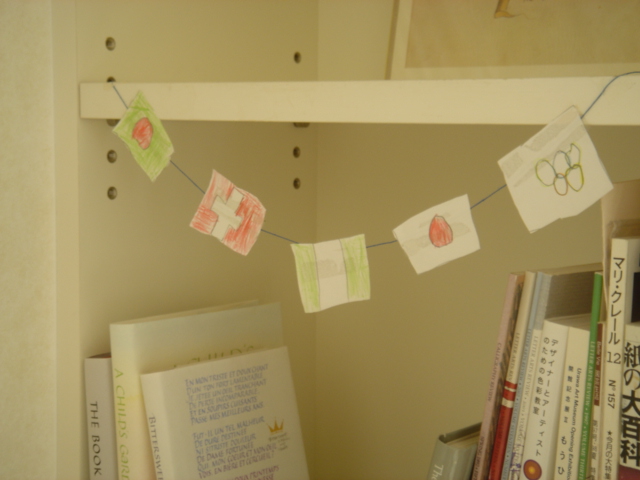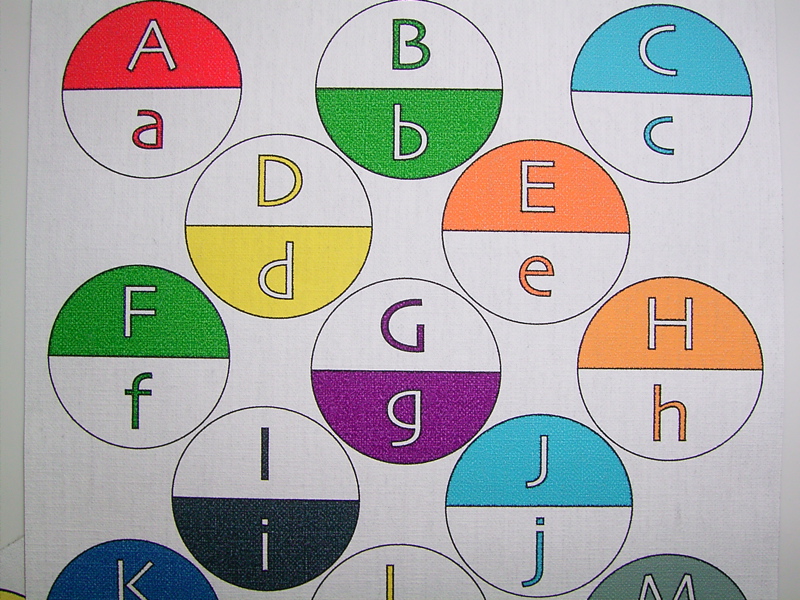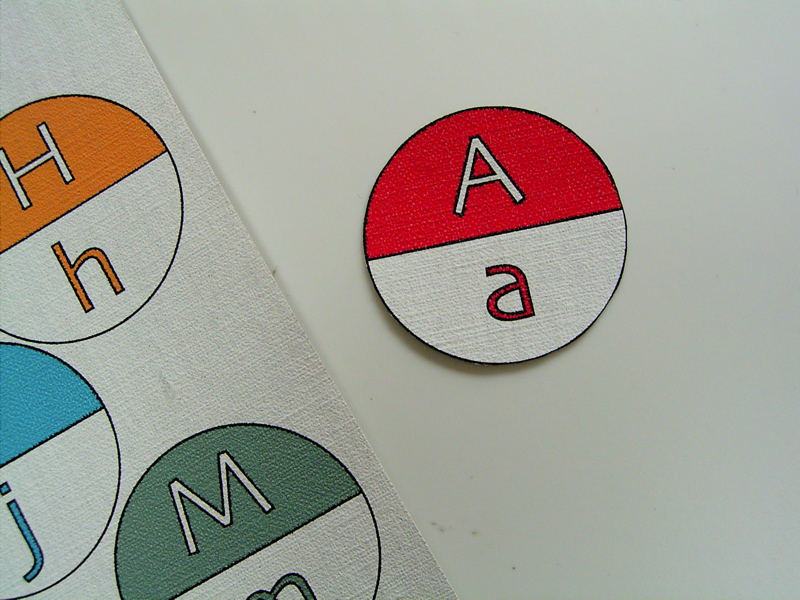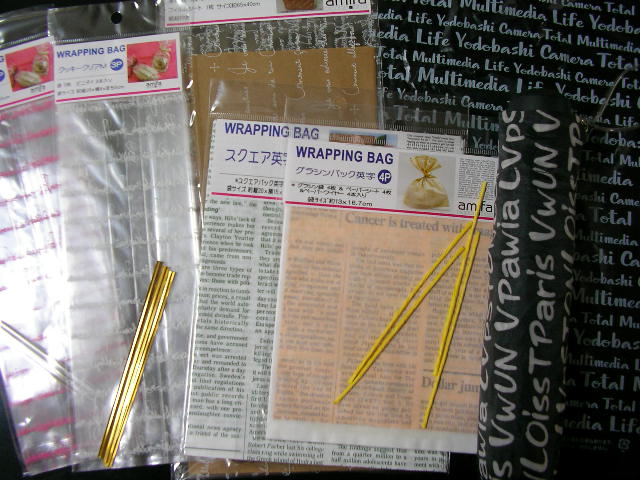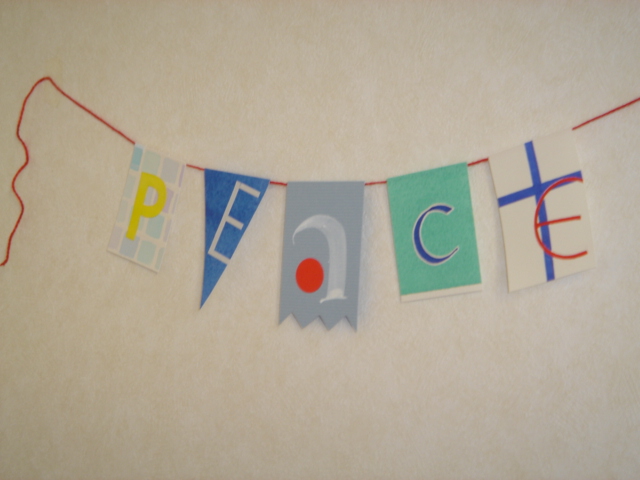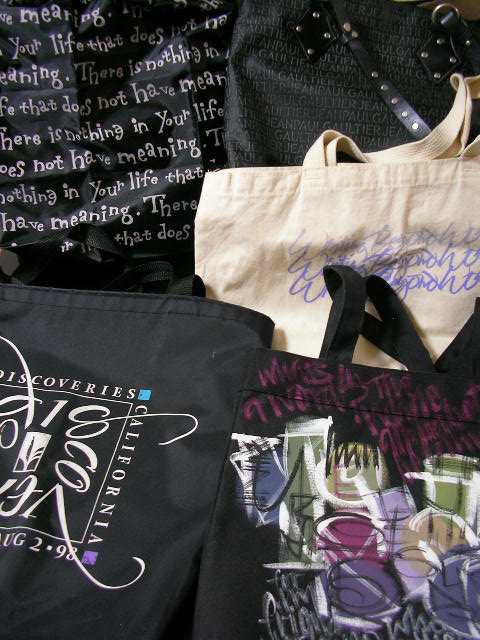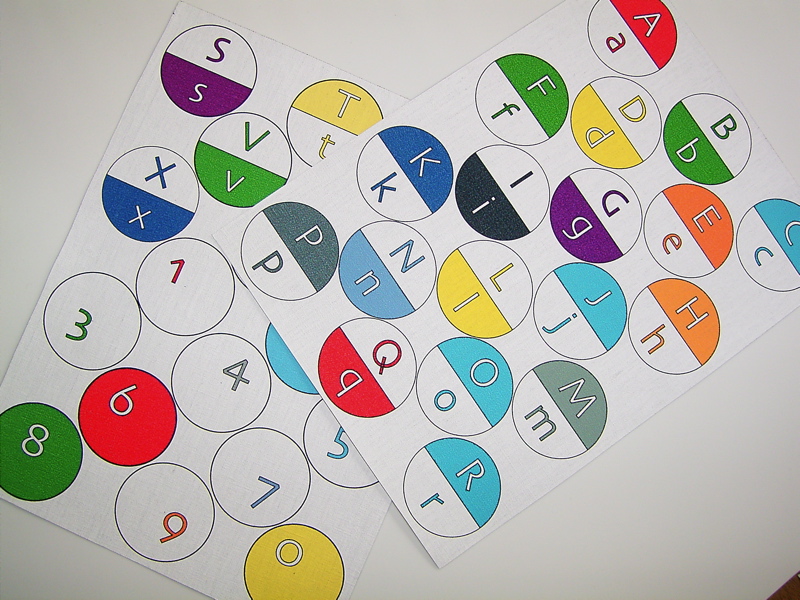
旗のアルファベット
もうすぐ運動会シーズンです。
万国旗がはためく下で、みんな懸命に練習した成果を披露するわけですね。
万国旗ってカラフルで心ウキウキするアイテムですよね。これはイメージを借りて作ったカードです。
こっちは以前子どもが作ったもの。親子して5枚が限度・・・?オリンピックを見ながら作っていたような記憶あります。
思い出ということで本棚にまだテープではったままにしてます。
さて、今年の夏はカーフェリーでお出かけしたのですが、そのヒマでヒマでたまらない航海中、操舵室見学というのがあったんです。チャチャッと案内されるだけなのかと思ったら結構ゆっくり見学させてもらい、説明も詳しくてレーダーで他の船の位置を見たり、楽しい時間を過ごしていました。
ふと気が付くと、部屋の端っこにAlphabet Flagsと書かれた紙が貼ってあるのが見え、突進。
アルファベットとあればなんでも反応してしまいますねー。
それは船の信号旗の早見表のようなものでした。さまざまなデザインの旗が並んでいて、それにA,B,C・・・とアルファベットがついています。
早速質問してみると、これら一つ一つに意味があり(たとえばオーなら「人が海に落ちました」とか!)これら単独、または組み合わせて信号とするのだそうです。
実際の旗はクルクルッと丸めて、細かく区切られた棚にしまってありました。(もちろん使うそうです)
使う旗はだいたい決まっているとのことでした。他に数字をあらわす旗もありましたよ。
知らない世界、またまたへぇー、でした。
袋もの
まだ幼かったころ、日々の食料を買いに行く時はかごを持参。ポッケタブルの袋なんてまだ珍しかったなあ〜。折りたたみのナイロンの手提げが売り出され、母が持ち歩いていた記憶。その後、見かけなくなってしまいましたが、時代の流れの中、またここ最近、折りたたみの手提げなんてものが、多数出ていますね。私のバックには、100円ショップで買ったナイロンの袋がいつも折りたたんで入っています。買い物をひとまとめにしたいときは便利なんです。でも、レジ袋は不要ですにはしない私なので、ごめんなさい。
さて、手提げ袋いろいろは、mojitor-hさんが、フリーク?!手提げ好きだなあという認識がある私ですが、そんな自分もカリグラフィーのもの、とくにB4、A3サイズの練習用紙や、ファイルを入れるには、もっぱら布やナイロンの手提げ袋を使うので大小持っているわけです。Bun2で紹介されたKarenにいただいた手書きの手提げは、使うにはもったいなくて飾りものですが、一番使いやすいのは、98年のカンファレンスのグッディバックです。厚めのナイロン(かな?)のいい大きさです。幸い今だ健在、大切に使っています!それから重宝しているのは、以前、布の手提げ袋を作るのが好きという方にいただいた裏地もしっかりついた布袋。最近、もち手が擦り切れてちょっと心配。自分でも作れるといいのだけれど......ミシンが壊れてる..........
袋で、もうひとつ。100円ショップの雑貨、ラッピング用品には、レターものがいくつかあります。カリグラフィーをやっている人の中には、この文字なんかね〜と思う人もいるかもしれませんが、私は、けっこうかわいいと思って買ってしまっています。傘、上記のナイロン袋、クッキー様のシースルーの袋などです!カリグラフィー好きの人は、このようなものもすべて自分で作っちゃうのかも.....ですけどね〜
ブルー&イエロー
にっこりスマイルのミニクラフトパンチが人気あるらしく売り切れなのかしらと話していたところ、mさんが世界堂にたくさんあったから、と私の分も買って送ってきてくださいました。
そうそう、このかわいいゼリー容器入りが見たかった!開けるのがもったいなくて、まだ使えないでいるのですが・・・
そしてmさんが添えてくださったミニミニアコーディオンブック。15ミリ角です。ちっちゃいものクラブにようこそ〜だって中のページは、ミニサイズのアルファベットのパンチで抜いてあるんです。AからZまでですよ。
この26文字セットを購入されるとはすごいです。(世界堂で、だそうです)
抜いた文字がバラバラにならないように、BやDやOなど輪になっている文字はどこかが切れているんですね。ふんふん、納得。
このかわいいミニブックは青い表紙です。黄色のパンチにぴったんこ!
青い色と黄色の組み合わせっていいなあ。スウェーデンの国旗の色が大好きなんです。
伝説によると昔々の王様が青空に金の十字架の光を見たことからこの国旗ができたそうなんですが・・・黄色ではなくて金色なんですね、ほんとうは。
以前見た北欧の学校の写真で、壁や掲示版なども青色で、そこに木の机や椅子があっていい色だなあと思っていました。この組み合わせが映える、その土地の空気ってあるかもしれません。
この二色の組み合わせは画家のモネのお気に入りだったとか。庭の花の組み合わせ以外にもインテリアや食器に使っていたらしいです。
この色が主役のお話といえば、レオ・レオー二の名作「あおくんときいろちゃん」ですね。お話も、絵も、このシンプルさがいいですよねー。
この絵本、実は表紙がすてき。本屋さんにあったらそっとカバーをはずして見てみて・・・もいいですか、本屋さん?
キャンバスアルファベット
以前、ホビーショーへ行った時、めざとく見つけたこのアルファベット。キャンバス地に印刷してあります。
カラフルで可愛いけど一体に何に使うのでしょう。まぁ、それはあとで聞くとして、とりあえずゲット。
大文字と小文字が円の上半分と下半分になっています。どうも、子供に英語を教える教材として利用するカードの代わりとなるものらしいですが、本当にそうだったか、もう今となっては忘れてしまいました。
でも確か、切り離して使いますって店頭のお兄さんは言っていたので、とりあえずハサミで切ってみました。
・・・・・で、なんだか小さなコースターみたいになりました。それとも丸いカルタの札?
シンプルな大文字と小文字のアルファベットがとにかくいい感じ。これで小学生たちは何を覚えるのやら。先生が「はい、AはappleのA!」と言ったら「ハイ!」といいながらこの札を取るのかしら? でもそれが一体なぜホビーショーで売られていたのかな?・・・確かキャンバス地に印刷できるのが画期的と言ってたような気がしますが、そうだったかしら〜(?Mojitor-hさんも一緒だったので彼女なら覚えているかも)
まぁ、使い道がなんであろうと、アルファベット大好き人間たちには嬉しい!これから何に使うか楽しみに考えます。
ABSEAS (ABC's) スタンプ
さぁ、一体このめっちゃ可愛い箱はなんでしょう〜
よ〜く箱を見て下さい。ABSEAS スタンプと書いてあります。ABC'Sと海をかけているんですね。もうこれを見ただけで、期待大でしょう〜?そう、これにはスタンプが入っています。しかもアルファベットです。26文字と数字と句読点やクエスチョンマークなどのパンクチュエーションも入ってます。
木のスタンプの先にゴムを貼る様に出来ています。本当の木です。もー可愛すぎる!画像ではわかりませんが、木のスタンプを持ちあげると、箱の底にタコやお魚が書いてあるのです。
そして文字も実に手書きっぽい。しっかりしたセリフがついている
この死ぬほど可愛いオランダの雑貨を探して来てくれたのは、Kさんです。知り合いの方がなさってる雑貨屋さんで見つけたそうです。みせてもらって、ドキュ〜ンと一目惚れ。
すぐに私も欲しい!とお願いして購入して頂きました。
そ・し・て! もっともっと嬉しかったのは、この箱を裏を見た時。
オランダの雑貨なのですが、どうもアメリカにもその会社はあるらしく、アメリカの住所が書いてありました。
ナントー!Oregon Eugene ! (オレゴン州、ユージーンと読みます)
そうでーす。私が住んでいた街でしたー。 それだけでハッピーな一日でした〜。